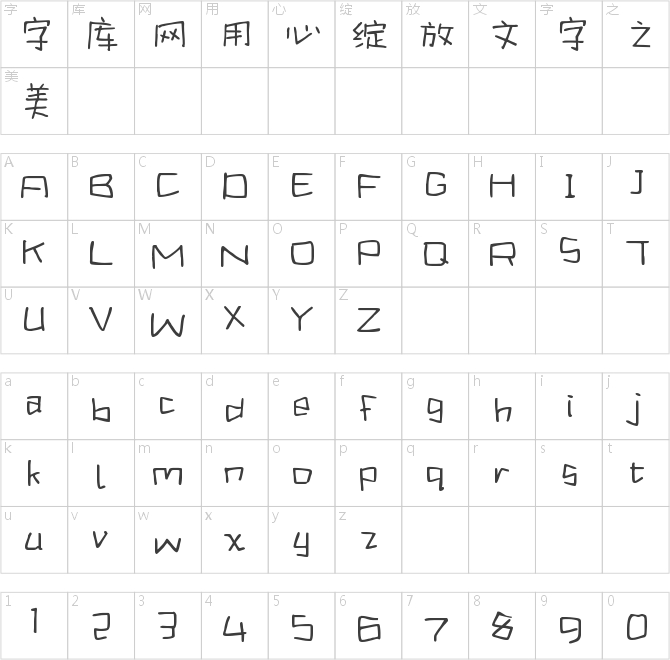
字體名稱: Aa幻想
Aa幻想
Aa幻想介紹
Aa幻想字體幻想字庫(kù)是一款讓人賞心悅目、百看不厭的中文字體,適合各類廣告和產(chǎn)品包裝設(shè)計(jì)應(yīng)用,字體大小7.63MB,格式為ttf字體,上傳用戶是Aa字庫(kù),作者/版權(quán)方為Aa字庫(kù)